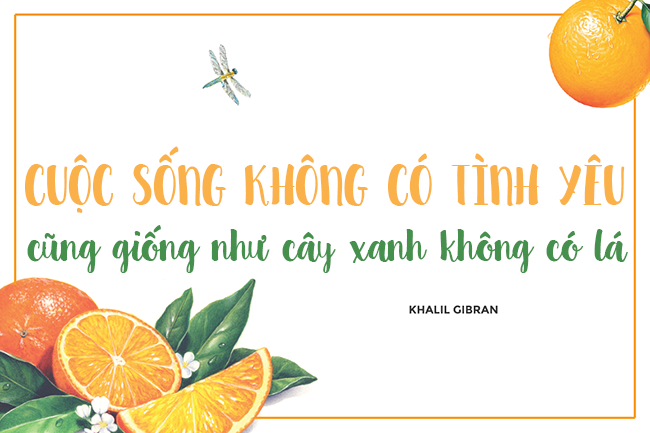
Clementine Script là một kiểu chữ thủ công mới mẻ, tươi tắn và đầy năng lượng. Font được phép sử dụng cho cả mục đích cá nhân và thương mại. Bạn có thể tải về và dùng Clementine Script cho bất kỳ dự án nào. Kiểu chữ này được lấy cảm hứng và thiết kế bằng bút dạ đầu vát cỡ lớn. Nét chữ đậm giúp logo trở nên nổi bật, rất phù hợp cho bảng hiệu, poster, logo, tiêu đề và nhiều ứng dụng khác.
Nhà thiết kế: Emily Spadoni
Nhà phát hành: Sweet Type